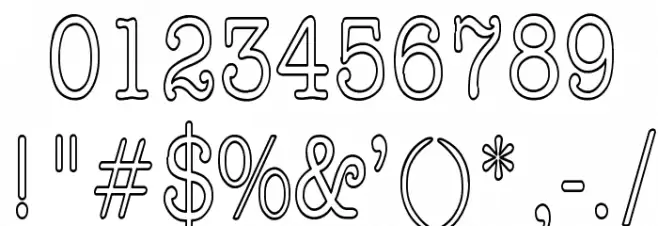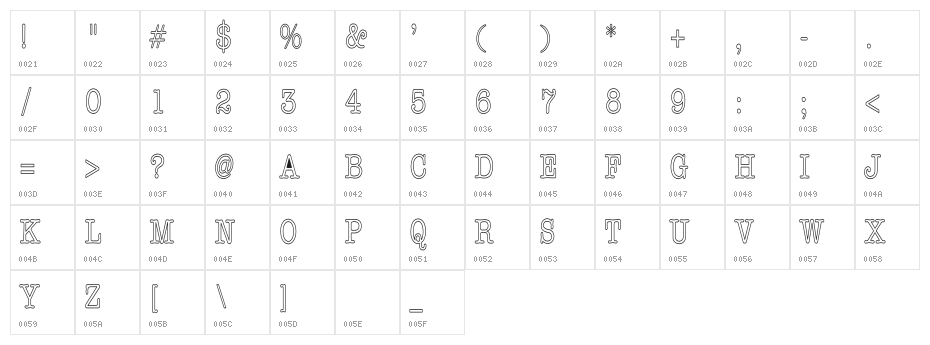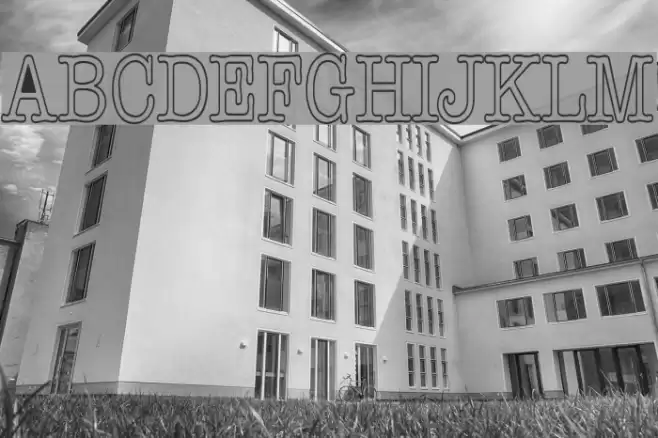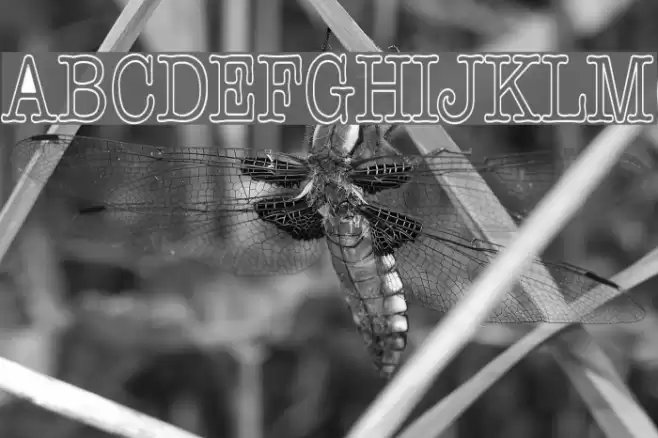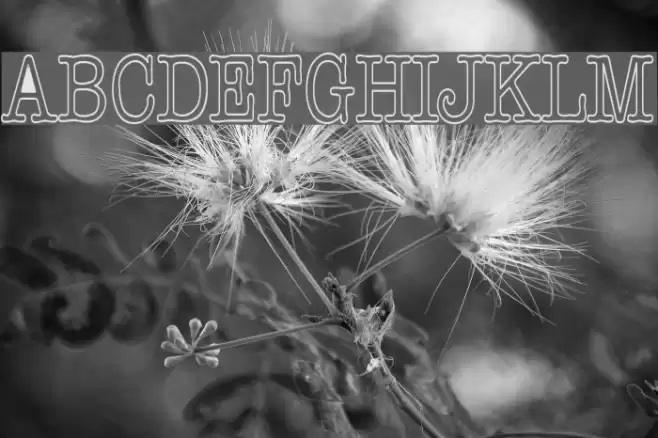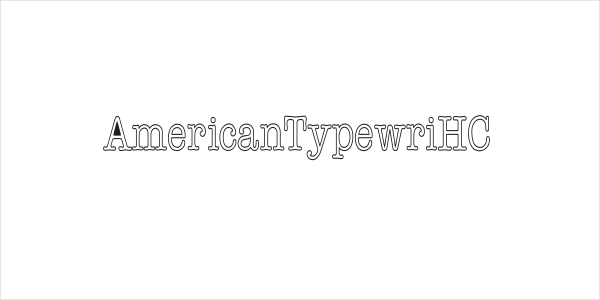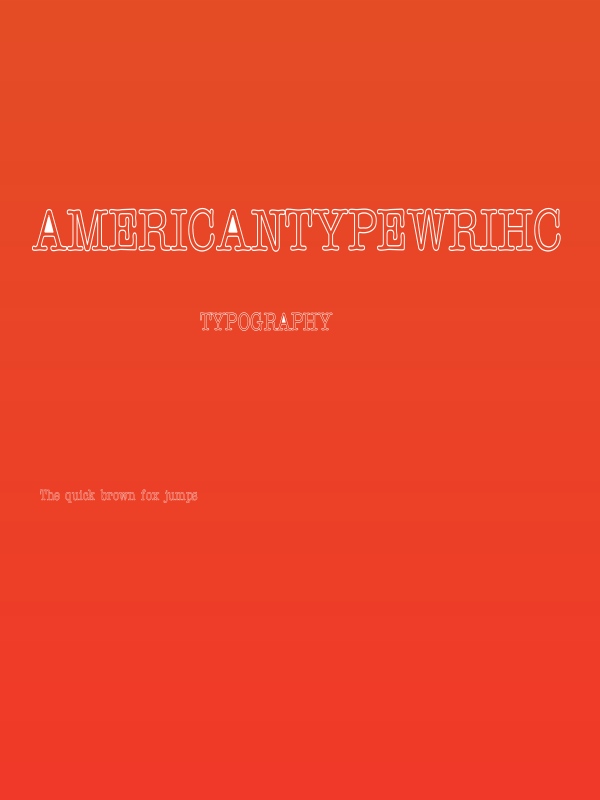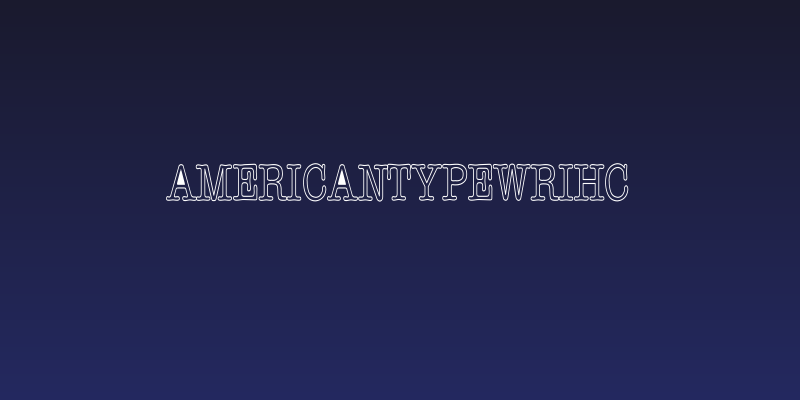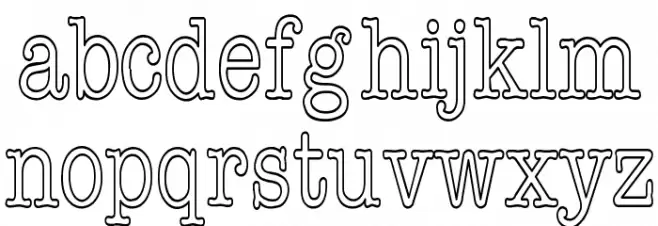
AmericanTypewriHC Font
| Projetos propostos | Ideal for retro-themed designs, typewriter-style documents, vintage posters, and creative projects that require a nostalgic touch. |